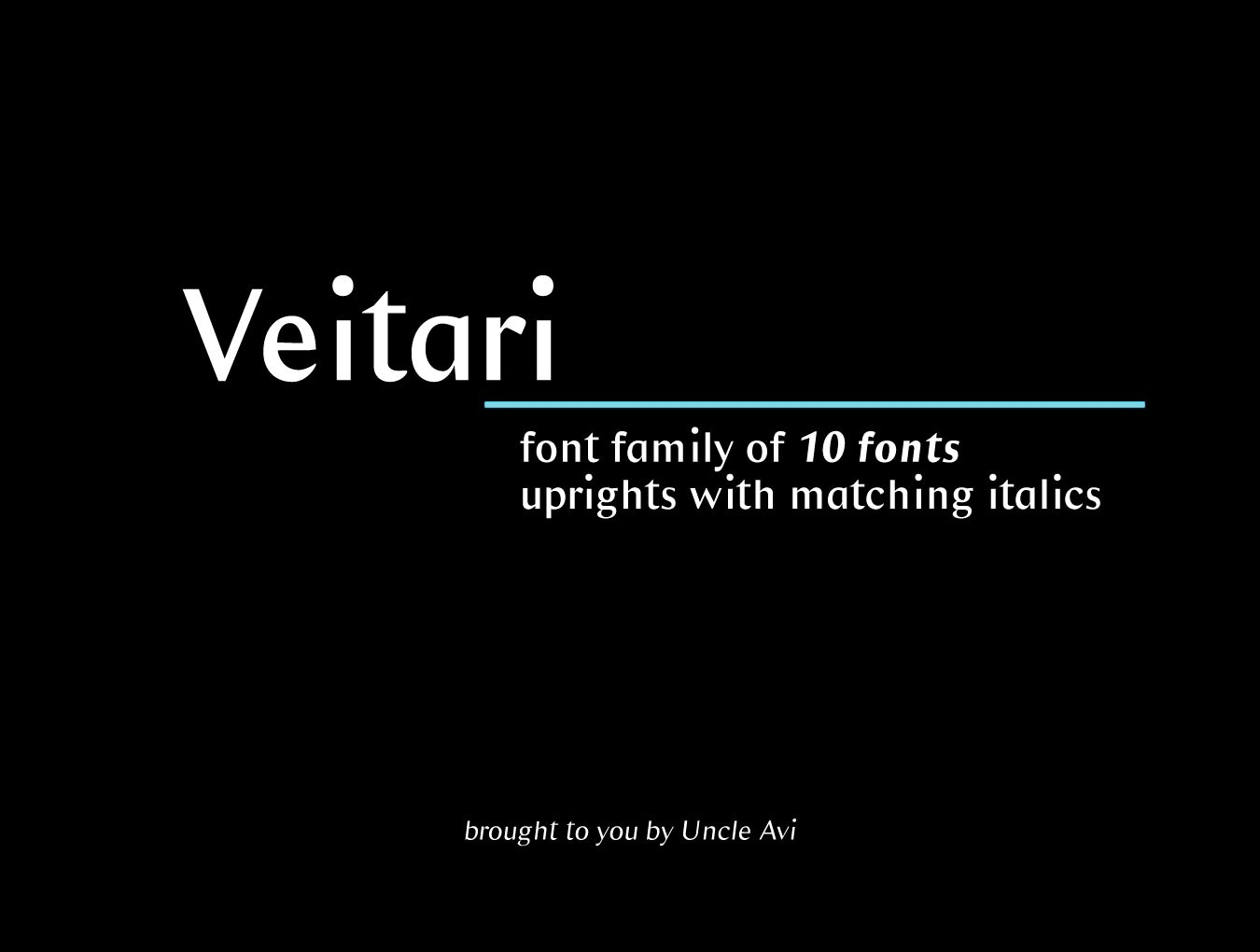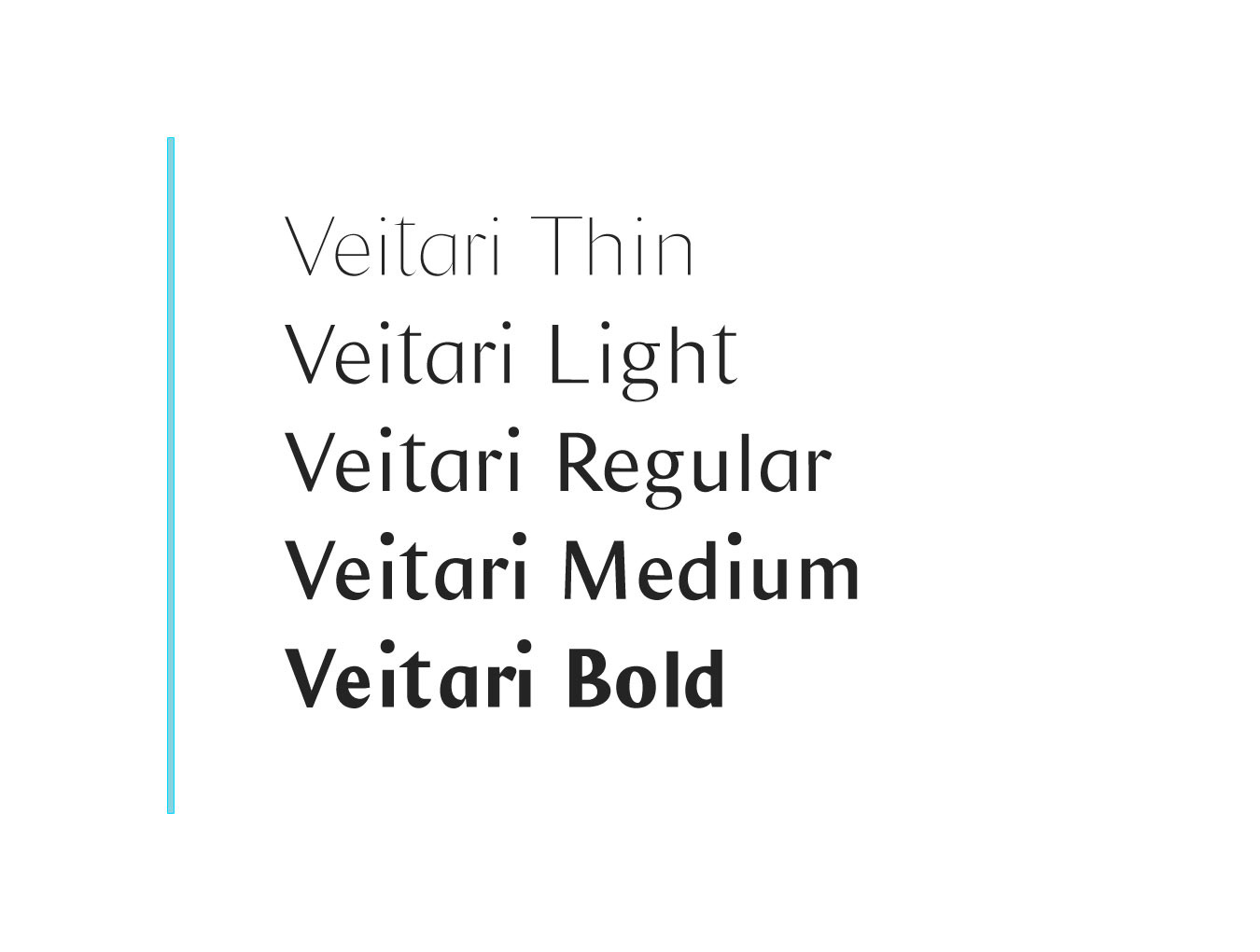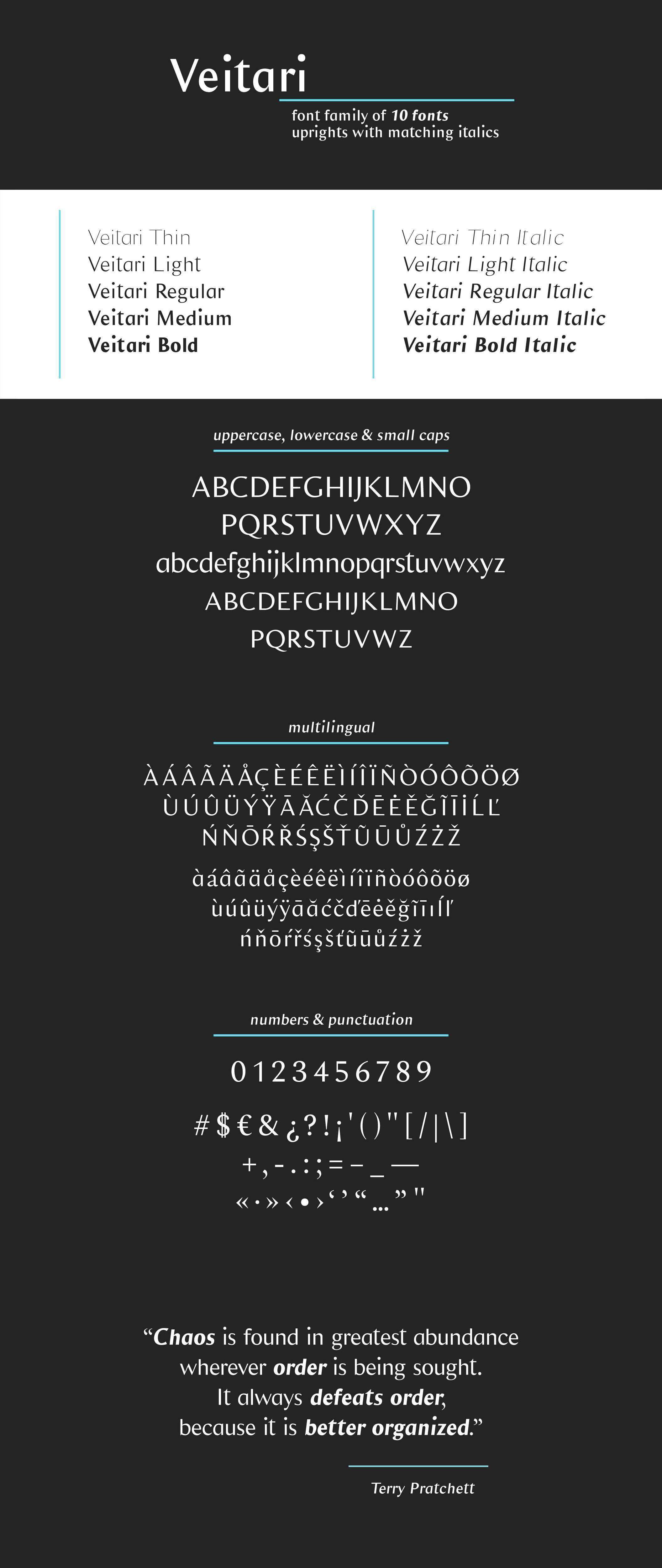
10 TTF字体,Veitari字体家族的集合
Collection of 10 TTF Fonts, Veitari Font Family
Veitari字体是10种字体的集合 - 立式与斜体匹配。这是优雅的无衬线字体家族,灵感来自旧笔灵感字体。 字体包含带有多语言支持的大写和小写字母。你会在这里找到数字,标点符号和小型大写字母。